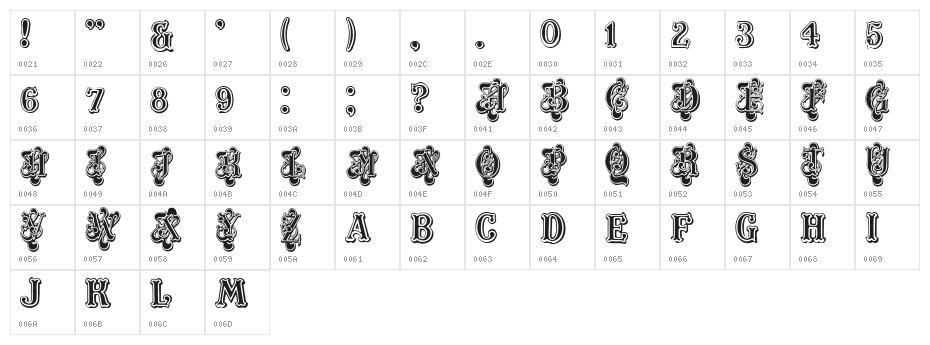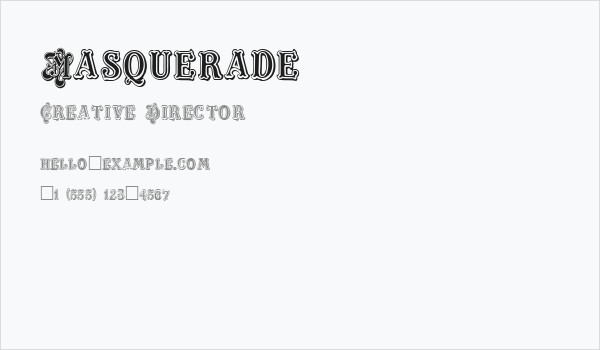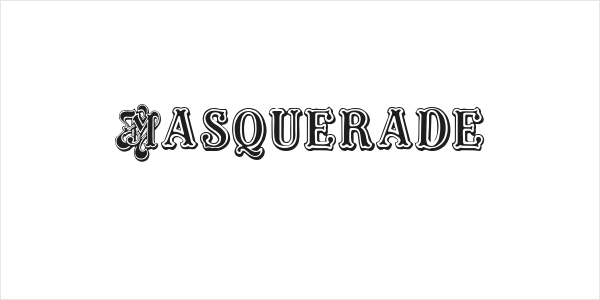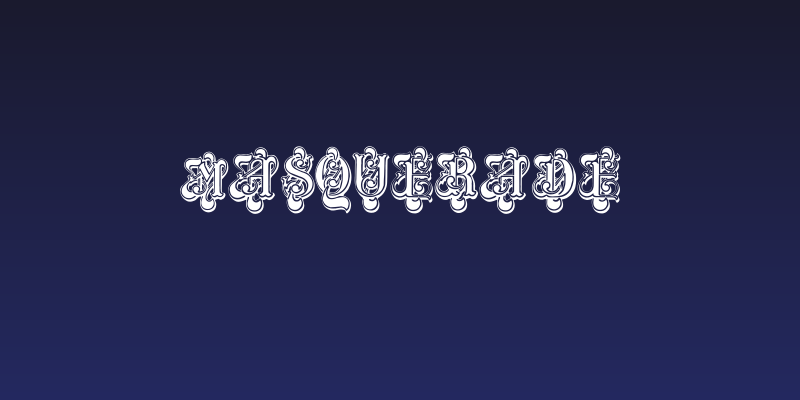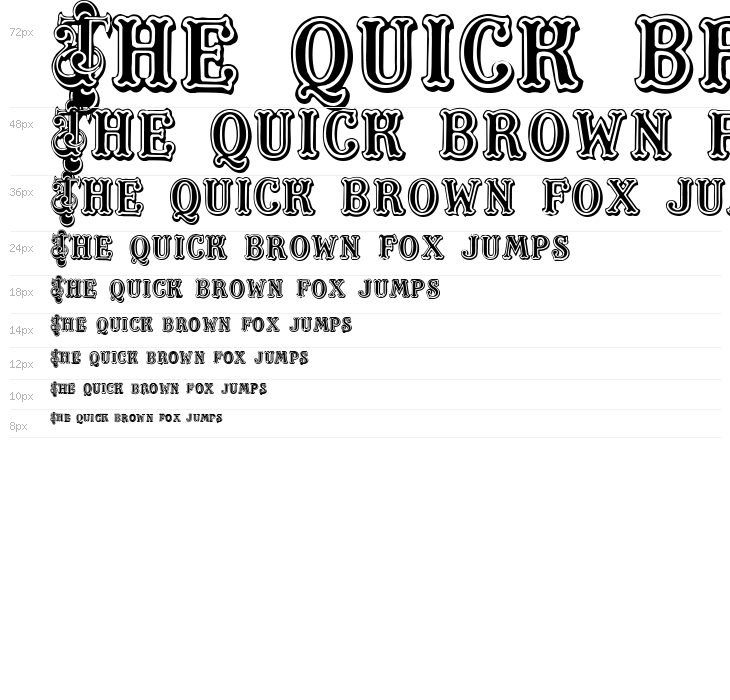
Masquerade Font
| Gesamtstil | Vintage |
| Vorgeschlagene Projekte | Ideal for vintage-themed posters, event invitations, branding for luxury products, or any project needing a touch of elegance and drama. |